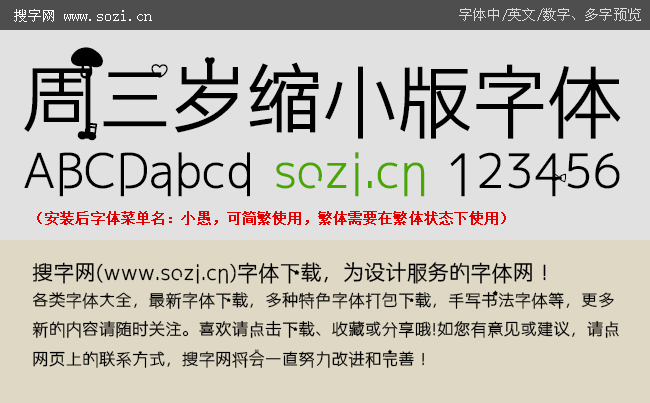
周三歲縮小版字體
搜字網(wǎng)給大家提供一款周三歲縮小版字體手機(jī)中文字體下載。這款手機(jī)字體是以黑體字體為原形,字體進(jìn)行了一些簡單變化,筆畫間又嵌入了可愛的卡通圖案。具有黑體端正易認(rèn)的風(fēng)格,卡通味也特別濃,特別適合喜歡手機(jī)字體個(gè)性一些的朋友在手機(jī)上安裝使用。